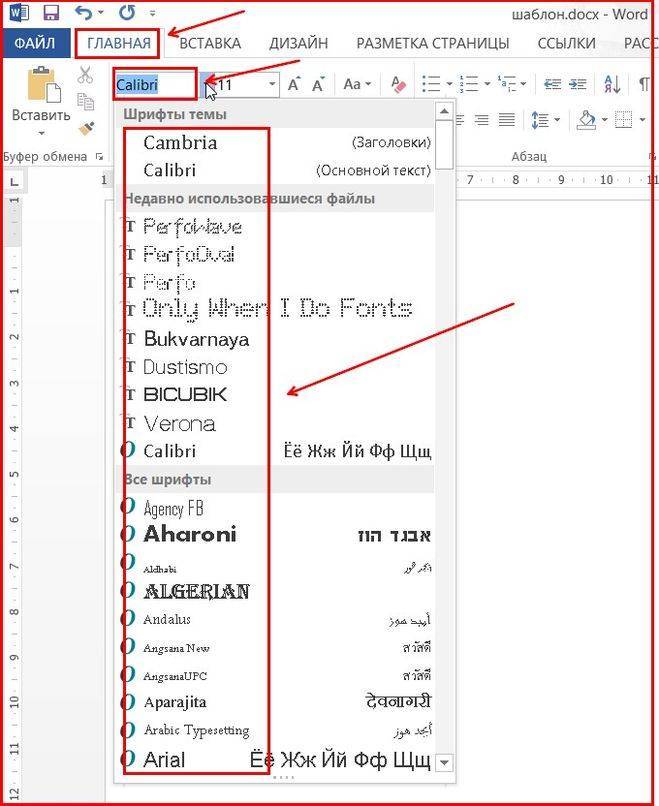
Microsoft хочет, чтобы вы выбрали новый шрифт по умолчанию для документов Word
Брайан Томас / Getty Images- Команда разработчиков Microsoft просит типографофилов проголосовать за новый шрифт по умолчанию для Office 365.
- Команда поручила дизайнерам сделать 5 новых вариантов: Tenorite, Bierstadt, Skeena, Seaford и Grandview.
- Классический Times New Roman не является вариантом и не используется по умолчанию с 2007 года.
Подвинься, Калибри, в городе появился новый шрифт, но какой из них выберут избиратели.
В среду команда дизайнеров Microsoft обратилась к типографистам с просьбой выбрать новый шрифт по умолчанию для программного пакета Office 365, в который входят основные приложения для рабочего места, такие как Word, Excel и PowerPoint.
«Шрифт по умолчанию часто является первым впечатлением, которое мы производим; это визуальная идентичность, которую мы представляем другим людям через наши резюме, документы или электронные письма. Мир вокруг нас стареет и растет, как и наши способы самовыражения», — говорится в заявлении команды.
Calibri был выбран брендом по умолчанию с 2007 года, когда он заменил классический Times New Roman.
И нет, Times New Roman не является одним из вариантов, за который можно проголосовать за обновление.
Пять новых вариантов без засечек называются Tenorite, Bierstadt, Skeena, Seaford и Grandview, и дизайнеры каждого из них представили свой лучший аргумент в пользу того, почему типографофилы должны выбрать их.
Дизайнеры Tenorite Эрин Маклафлин и Вей Хуанг сказали, что «нам нужно что-то очень круглое, широкое и хрустящее».
«Поскольку клиенты читают и пишут длинные абзацы текста в таких приложениях, как Microsoft Word, более широкий интервал между символами полезен», — сказали они.
Bierstadt вдохновлен «гротескными» шрифтами, которые в типографских терминах относятся к печатным буквам, лишенным причудливых завитков и контрастной толщины линий.
«Я считаю, что в современном мире голос гротескного шрифта нуждается в небольшом количестве человеческого прикосновения, чтобы казаться более доступным и менее институциональным», — сказал дизайнер Стив Маттесон.
Сотрудничая с Джоном Хадсоном для Skeena, Пол Хэнслоу «хотел выбрать из нескольких типографских периодов и заставить их работать вместе».
Нина Штёссингер, которая работала с Тобиасом Фрер-Джонсом и Фредом Шалкрассом, сказала, что ее вдохновением для Сифорда послужили фотографии старых кресел.
Аарон Белл позаимствовал из более раннего шрифта, который он разработал для создания Grandview, который, как он утверждает, будет иметь «лучшую разборчивость и читаемость при меньших размерах на устройствах с низким разрешением».
Все пять шрифтов теперь доступны в облаке Office 365, а на странице компании в Твиттере приветствуется обратная связь в социальных сетях.